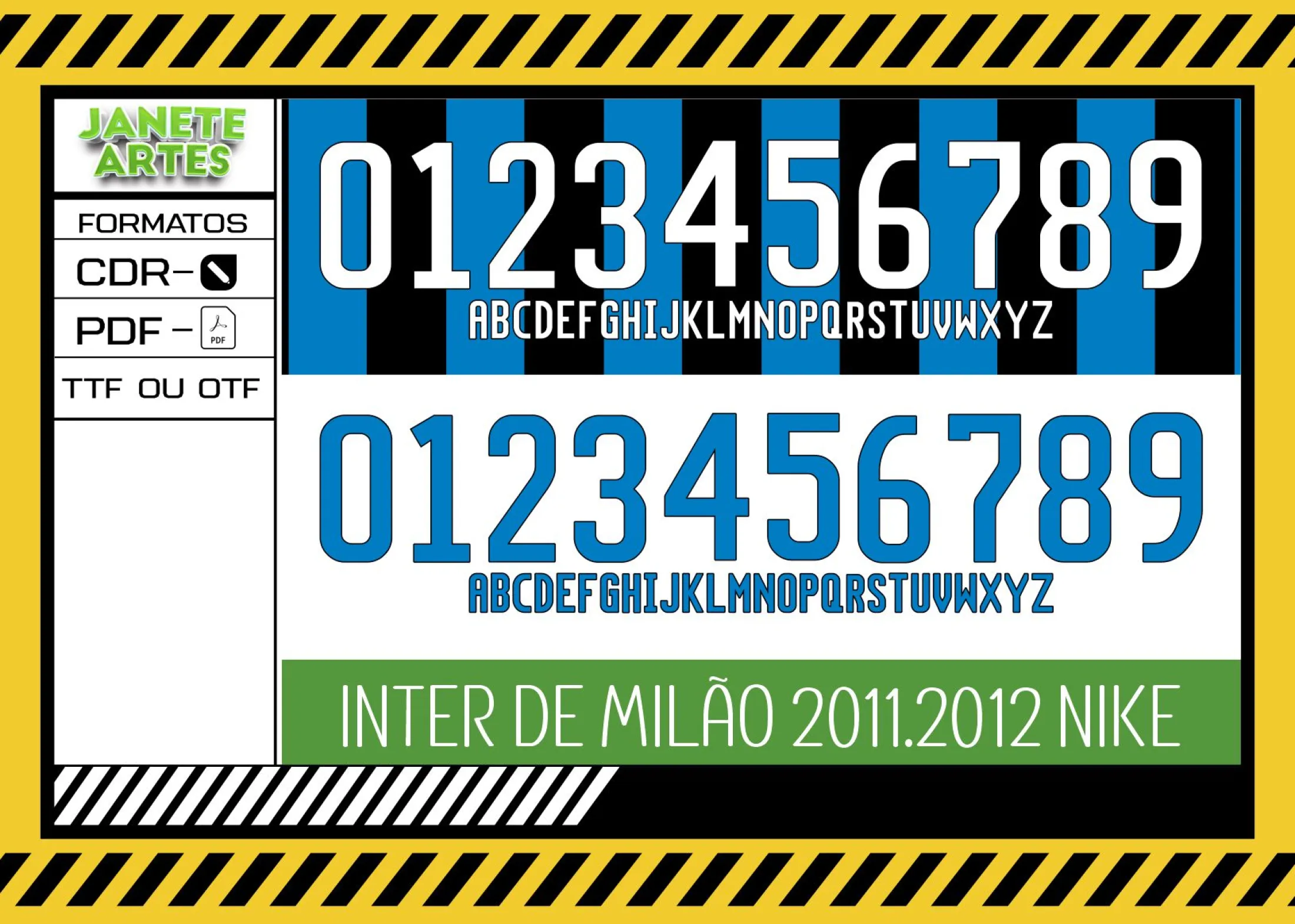
Fonte de Time Tipografia Inter de Milão 2011 - 2012
Descubra o design da Fonte de Time Tipografia Inter de Milão 2011 - 2012 para criar camisas únicas e estilizadas. Arquivo digital perfeito para personalizar camisetas e destacar seu estilo com autenticidade e personalidade.
Uma paixão que virou inspiração
Você já sentiu aquela vontade de capturar algo especial para contar sua história? Foi assim que nasceu a ideia por trás da Arte Fonte de Time Tipografia Inter de Milão 2011 - 2012 Camiseta Unissex. Tudo começou em 2011, quando um grupo de amantes do design de tipografia da Inter de Milão decidiu eternizar as letras do time de futebol em um projeto único. Essa fonte tornou-se símbolo de identidade e, anos depois, chegou a possibilidade de levar essa temática para o seu guarda-roupa, transformando camisetas comuns em peças cheias de personalidade e conexão com o mundo do esporte e design.
• Por que escolher essa tipografia? Ela traz autenticidade e estilo inspirados em um clássico time de futebol.